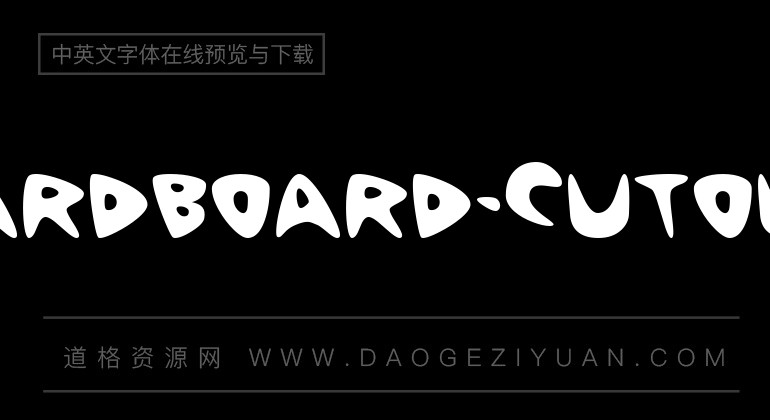
Cardboard-Cutout 是一款拥有独特纹理的英文字体,它的特点是字符的形状像是由硬纸板制成的,可以带来立体的效果。它的字体风格给人一种温暖的感觉,可以增添设计的趣味性和质感。Cardboard-Cutout 字体适用于所有设计作品,可以用于品牌标识,海报,T恤,海报,网页等等。它可以帮助你创造出与众不同的设计,并给你的作品带来独特的视觉效果。内容介绍
Cardboard-Cutout是一款非常不错的手写艺术字体,具有很好的视觉感,适合于文化类的宣传设计、商业类品牌的广告和产品包装设计以及个性化文字排版等较多场景。